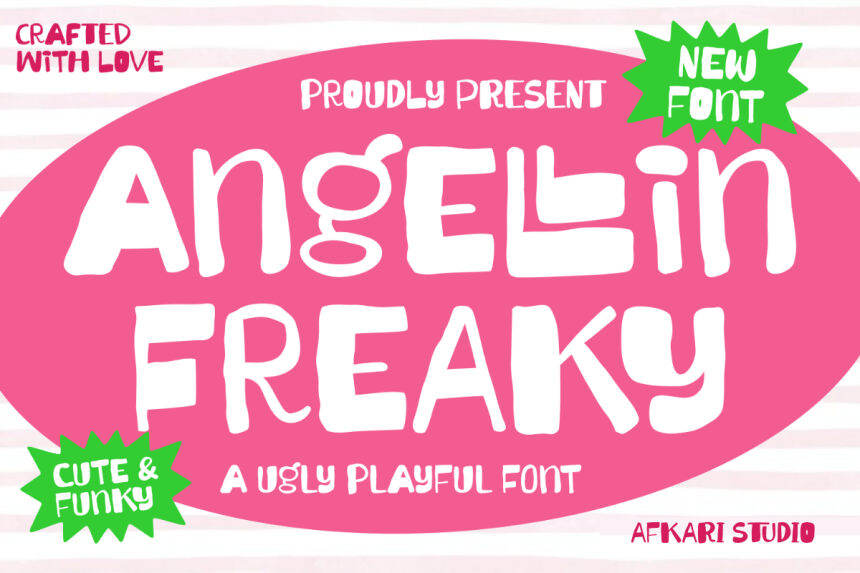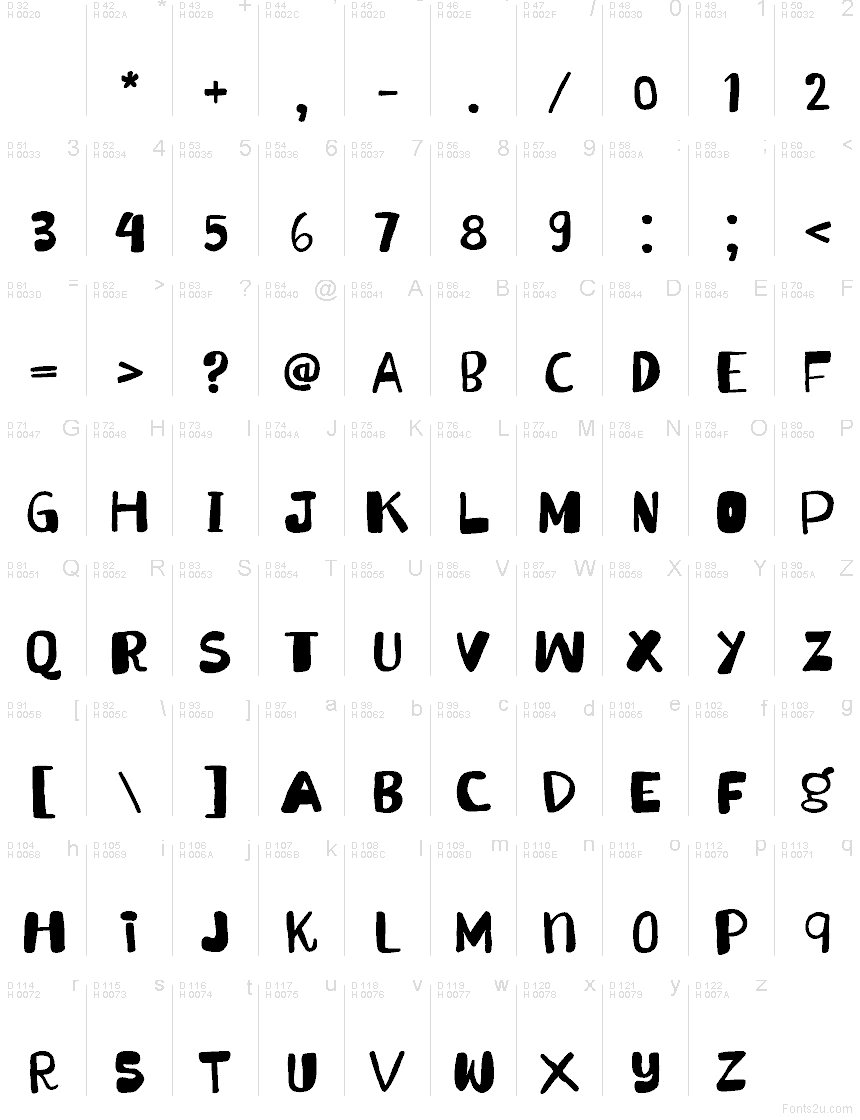
Angellin Freaky von Afkari Studio ist eine kostenlose Cartoon-Display-Schrift mit lockerem, handgezeichnetem Schwung und einer leicht schelmischen Note. Die Buchstaben kombinieren dicke, abgerundete Striche mit unebenen Kurven und verspielten Überhängen, was der gesamten Schrift einen krakeligen, unkonventionellen Rhythmus verleiht, der eher skizzenhaft als perfekt wirkt.
Sie eignet sich ideal für Jugendmarken, Snackverpackungen, Party-Flyer, Comic-Überschriften und verspielte Social-Media-Posts – überall dort, wo eine kurze Zeile ein wenig Quirligkeit statt klarer Geometrie braucht. Als kostenlose Schrift ist sie auch perfekt für Titelkarten, Poster und Logo-Skizzen, die einen lässigen, ausgefallenen Look suchen, ohne dabei ins Unordentliche abzudriften.